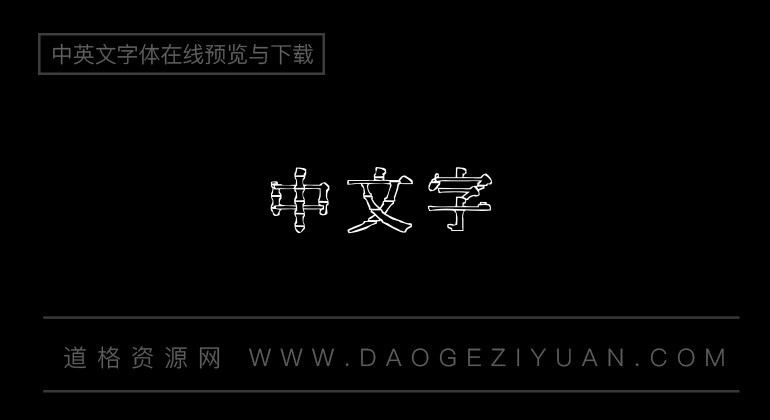
文鼎竹子体
文鼎竹子体是一种简洁优雅的中文竹子字体,由香港设计师文鼎设计。它的特点是字体背景有细节,笔画精致,每一字都有自己独特的风格,给人一种清新自然的感觉。文鼎竹子体拥有多种字号,可以满足不同的设计需求,是一种非常适合中文文案的竹子字体。
文鼎竹子体是一款非常不错的手写艺术字体,具有很好的视觉感,适合于文化类的宣传设计、商业类品牌的广告和产品包装设计以及个性化文字排版等较多场景。